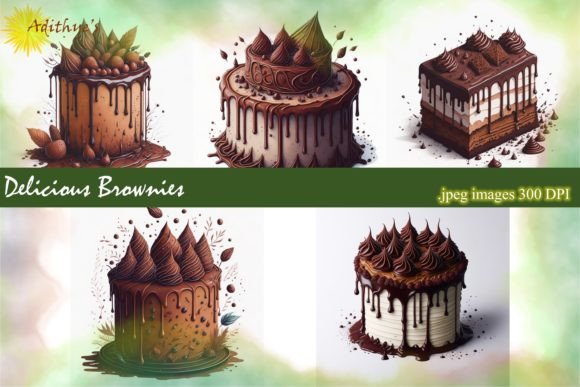
Delicious Brownies
การค้นหาองค์ประกอบการออกแบบที่เหมาะสมอาจเป็นเรื่องท้าทาย แต่ Delicious Brownies นำเสนอคอลเลกชันที่โดดเด่นซึ่งช่วยยกระดับงานของคุณได้ทันที
ไม่ว่าคุณจะสร้างผลิตภัณฑ์ POD (Print on Demand) คำเชิญงานแต่งงาน หรือกราฟิกโซเชียลมีเดีย Delicious Brownies ก็เหมาะสมอย่างยิ่ง